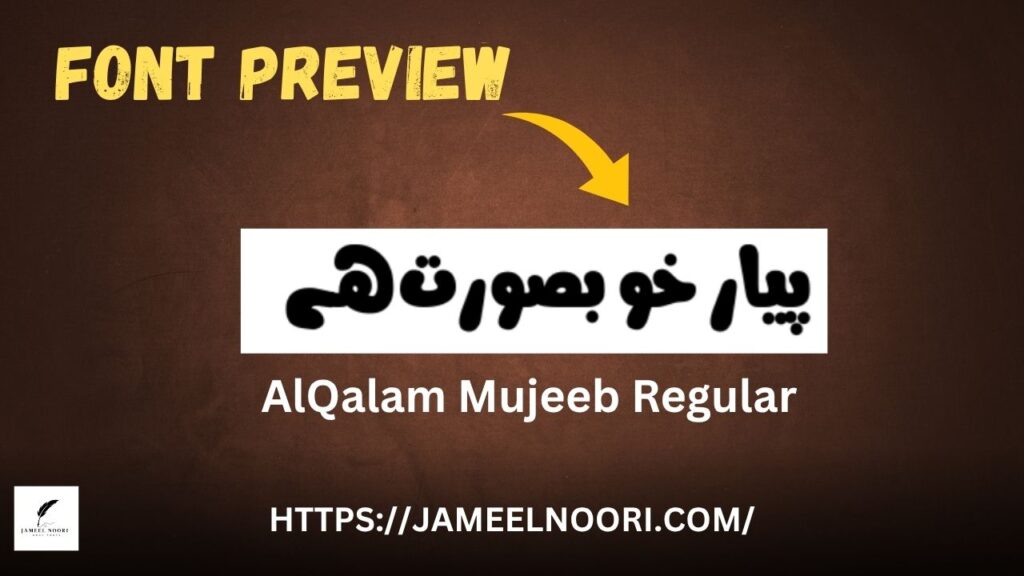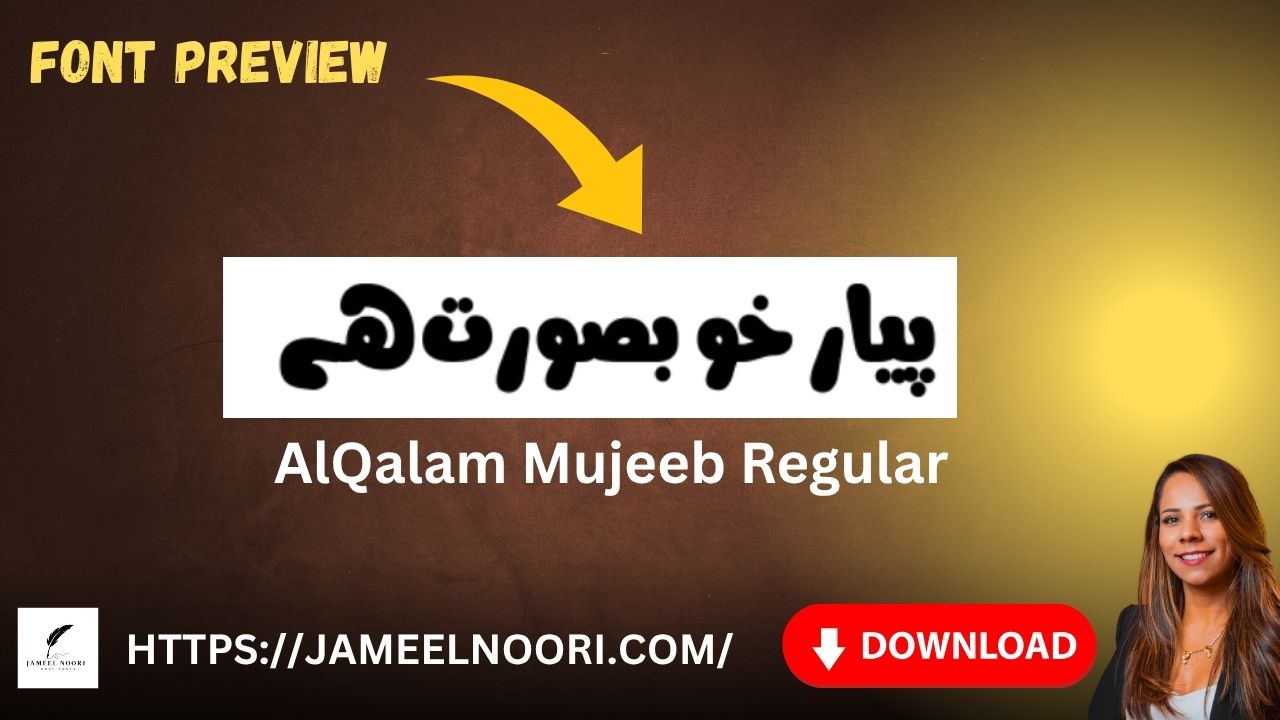
Introduction to Urdu Font AlQalam Mujeeb
Urdu Font AlQalam Mujeeb aik mashhoor aur reliable Urdu typeface hai jo designers aur Urdu content writers ke liye bohat useful sabit hota hai. Ye font khas tor par likha gaya hai taake aapka Urdu text elegant aur readable lage. Is article me hum apko is font ke bare me complete information dy gy taki aap bina time waste kiye is font ka best use kar saken.
Features of Urdu Font AlQalam Mujeeb
Urdu Font AlQalam Mujeeb ke kuch khaas features isay doosre fonts se alag banate hain:
- Readability aur smooth Urdu letter shapes provide karta hai.
- Printing aur digital design dono ke liye perfect hai.
Benefits of Using Urdu Font AlQalam Mujeeb
Urdu Font AlQalam Mujeeb ke kuch zabardast faide jo isay best Urdu fonts me se ek banate hain:
- Professional Look: Urdu documents aur books ke liye perfect.
- Easy to Read: Long paragraphs aur articles me clear readability deta hai.
Why Urdu Font AlQalam Mujeeb is the Best Choice
Agar aap Urdu typing, books, ya social media designs ke liye ek reliable aur stylish font dhoond rahe hain to Urdu Font AlQalam Mujeeb best choice hai. Ye font Urdu letters ko natural flow deta hai aur readability maintain karta hai. Designers aur publishers dono ke liye ye ultimate solution hai.
Aaj ke digital zamane me Urdu Font AlQalam Mujeeb designers aur Urdu content creators ke liye ek affordable aur best option hai. Iski readability, beauty aur professional appeal isay unique banati hai. Agar aap Urdu me likhna pasand karte hain to ye font aapke liye perfect hai.
What is Urdu Font AlQalam Mujeeb?
It’s a TrueType Urdu font used for writing and designing in Urdu with clear and elegant style.
Is AlQalam Mujeeb better than Jameel Noori Nastaleeq?
Both are great; AlQalam Mujeeb is simpler and lightweight while Jameel Noori is more stylish.
Is Urdu Font AlQalam Mujeeb good for graphic design?
Definitely! It gives a neat and professional Urdu look in designs.
Does it support all Urdu characters?
Yes, it includes full Urdu alphabet with special diacritics.